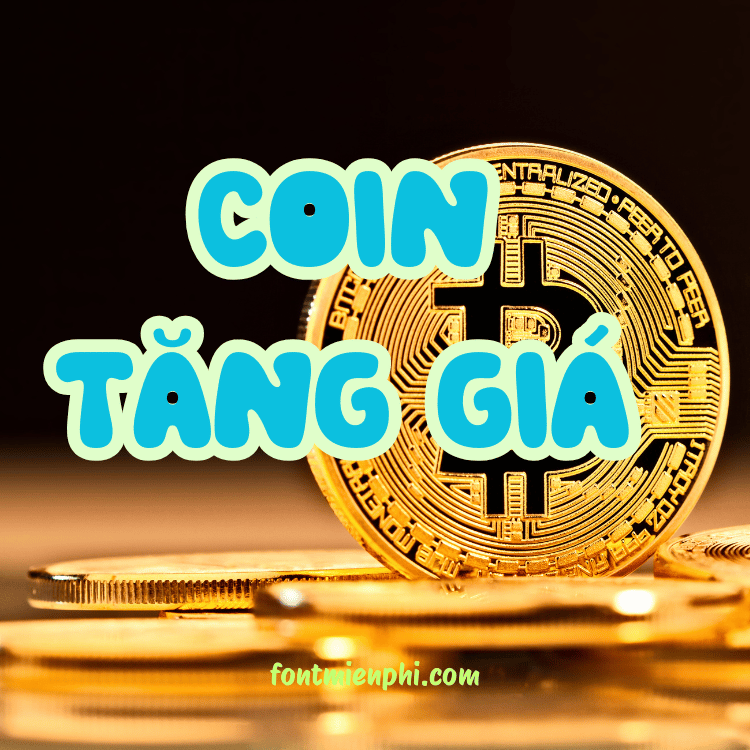
Font Việt hóa FMP Lucky vip
Giới thiệu về Font Việt hóa FMP Lucky vip
Trong thế giới đồ họa hiện đại, việc lựa chọn một Font Miễn Phí phù hợp là yếu tố quyết định đến sự thành công của một tác phẩm. Font Việt hóa FMP Lucky vip nổi lên như một lựa chọn hàng đầu nhờ phong cách thiết kế hiện đại, trẻ trung và đầy năng lượng. Đây là bộ phông chữ được tinh chỉnh kỹ lưỡng để hỗ trợ đầy đủ bảng mã tiếng Việt, giúp người dùng không còn lo lắng về lỗi hiển thị dấu khi soạn thảo văn bản hay thiết kế ấn phẩm truyền thông.
Đặc điểm nổi bật của bộ font Lucky vip
Bộ Font Việt hóa FMP Lucky vip sở hữu những đường nét bo tròn mềm mại nhưng vẫn giữ được sự cứng cáp cần thiết. Với cấu trúc chữ cân đối, bộ font này cực kỳ phù hợp cho các mục tiêu giáo dục, thiết kế bìa sách giáo khoa hoặc trang trí lớp học. Khả năng hiển thị sắc nét trên cả màn hình kỹ thuật số và bản in giúp các em học sinh dễ dàng tiếp cận nội dung bài học một cách sinh động nhất. Ngoài ra, tính ứng dụng cao của nó còn trải dài từ thiết kế logo, poster quảng cáo cho đến các thiệp mời sự kiện quan trọng.
Cách ứng dụng Font Việt hóa FMP Lucky vip hiệu quả
Để tận dụng tối đa vẻ đẹp của Font Việt hóa FMP Lucky vip, bạn nên kết hợp nó với các tông màu tươi sáng hoặc pastel để tạo cảm giác thân thiện. Trong môi trường học đường, giáo viên có thể dùng font này để làm slide bài giảng thêm phần hấp dẫn. Việc cài đặt font cũng rất đơn giản, chỉ cần vài thao tác giải nén và cài đặt vào hệ thống là bạn đã sẵn sàng sáng tạo.